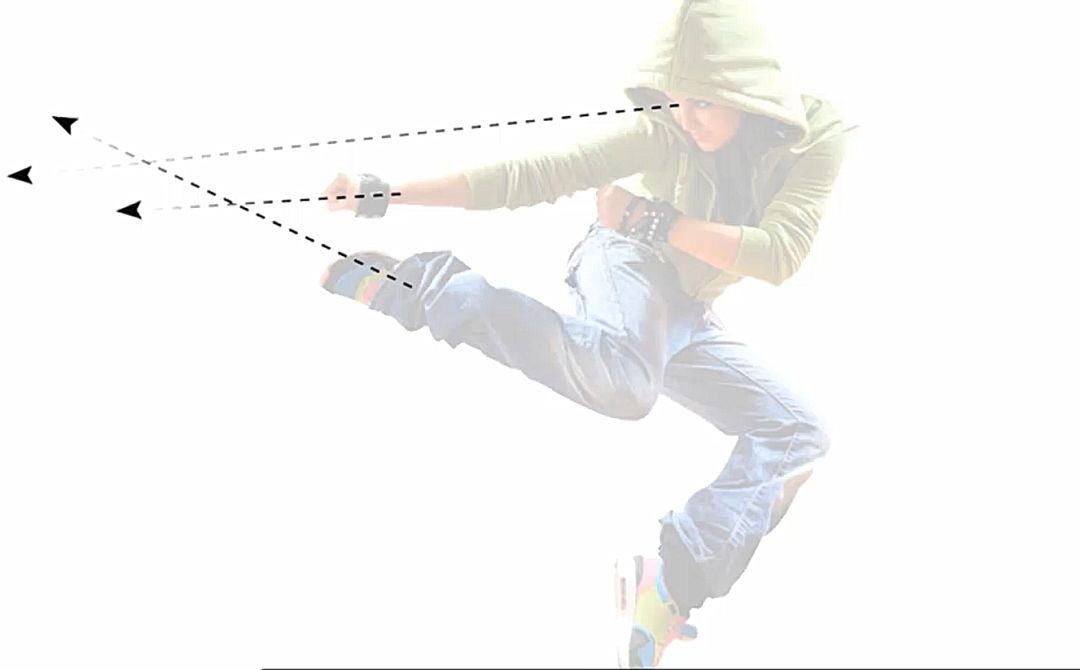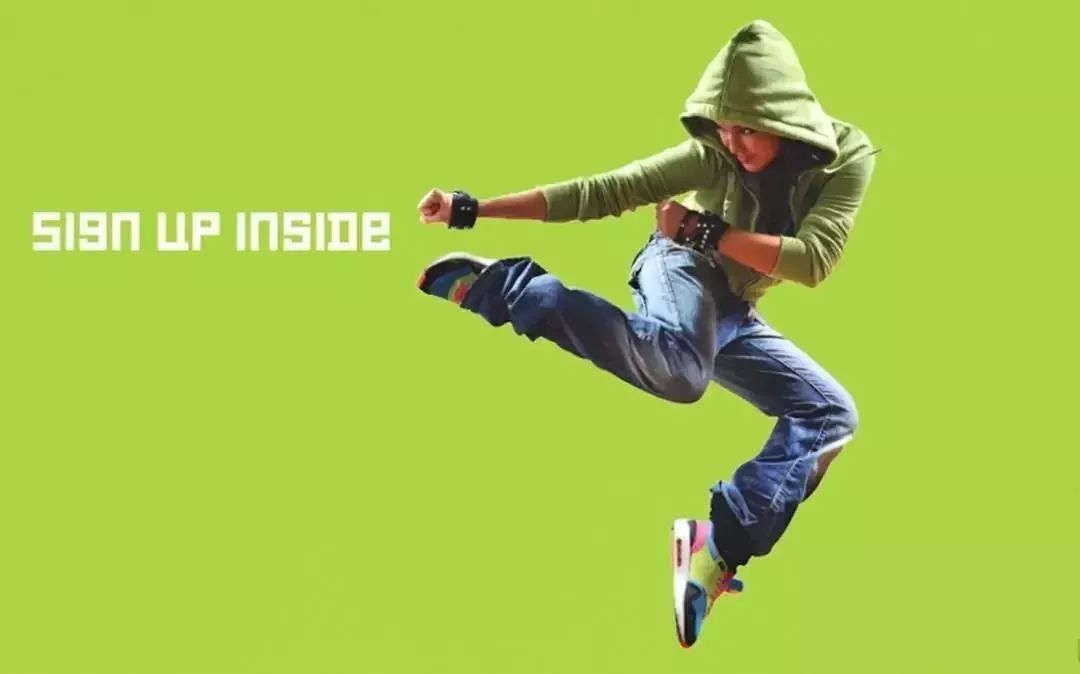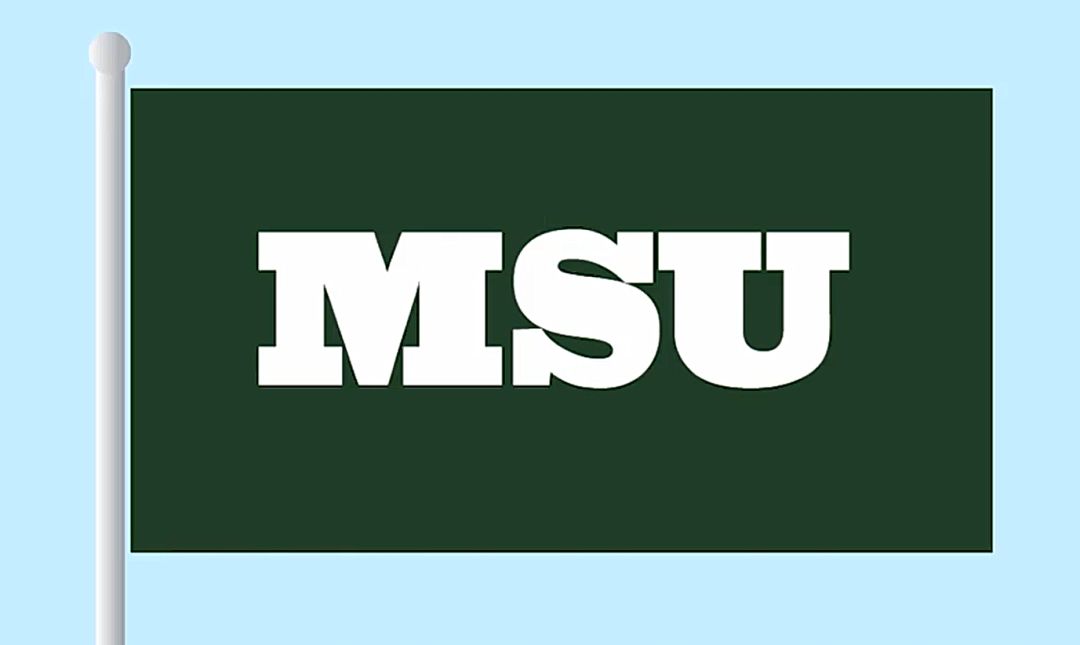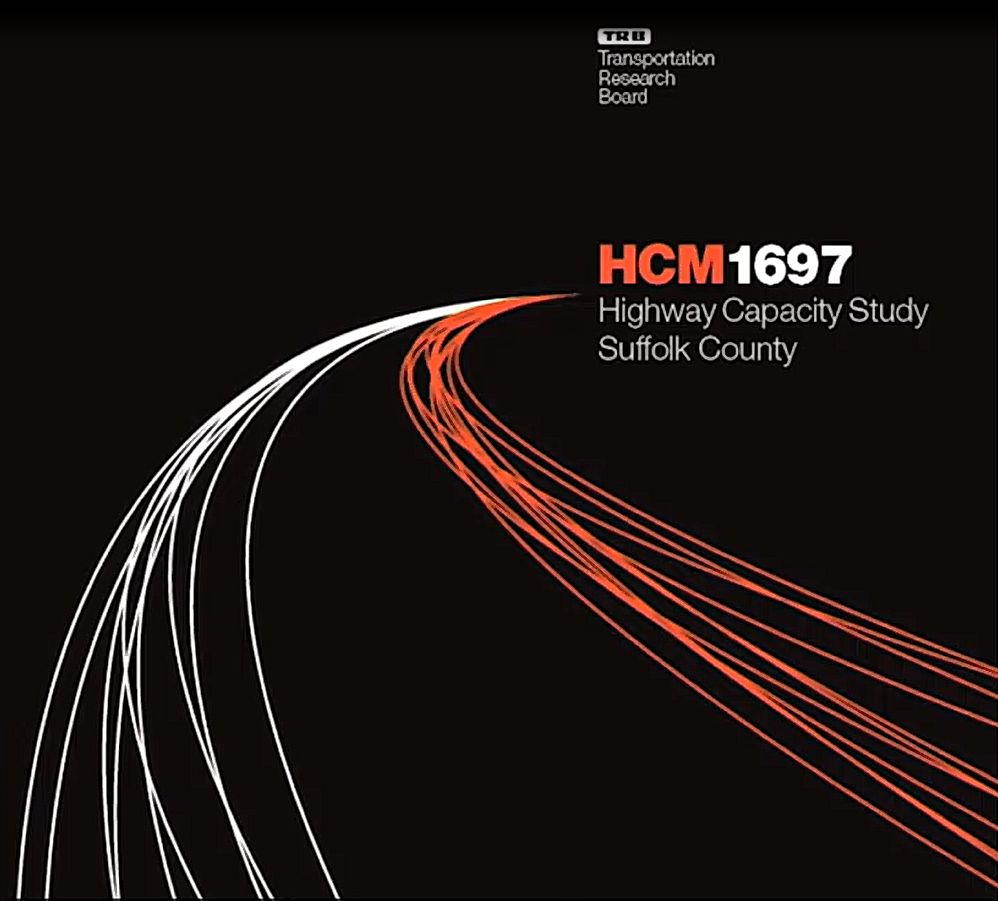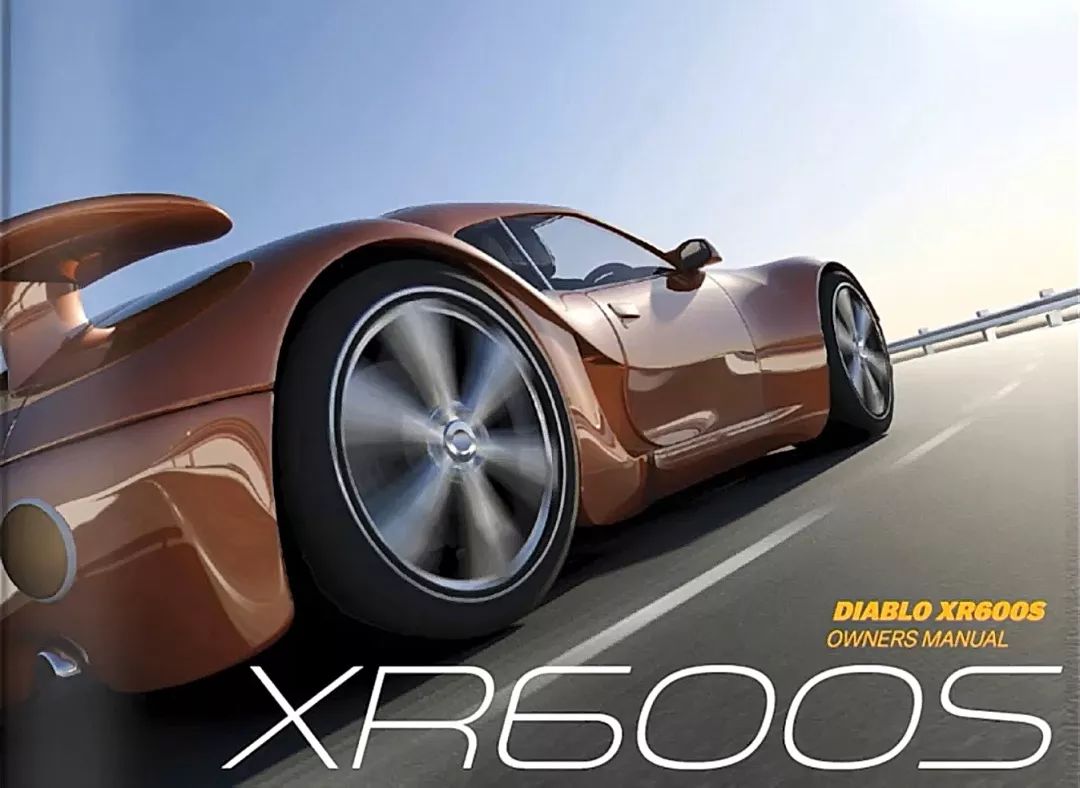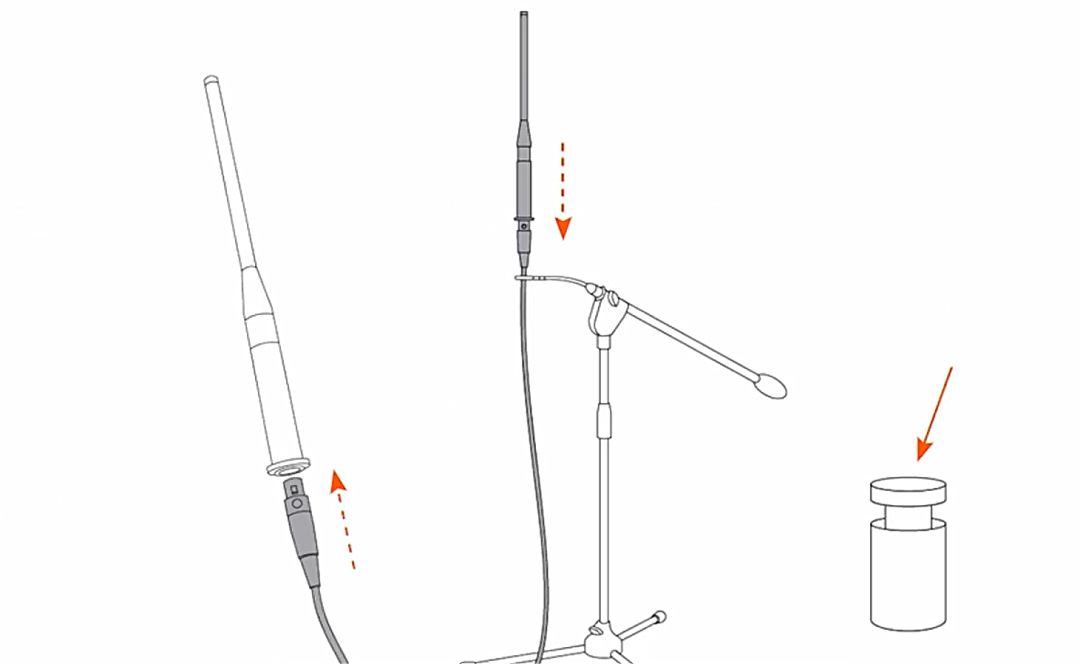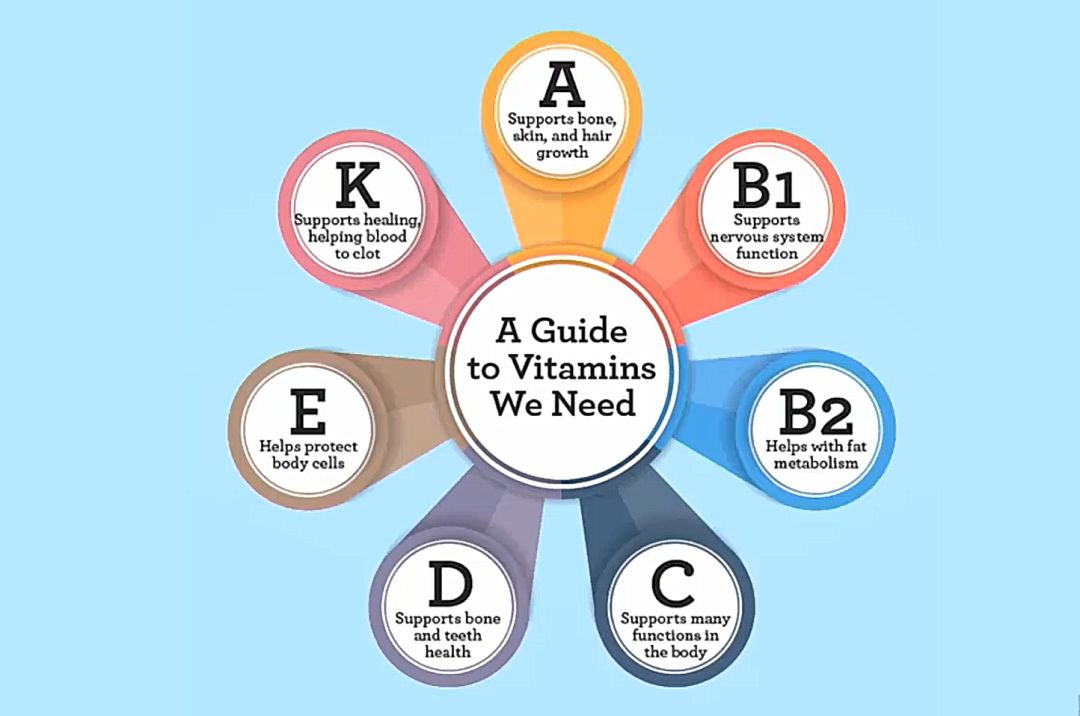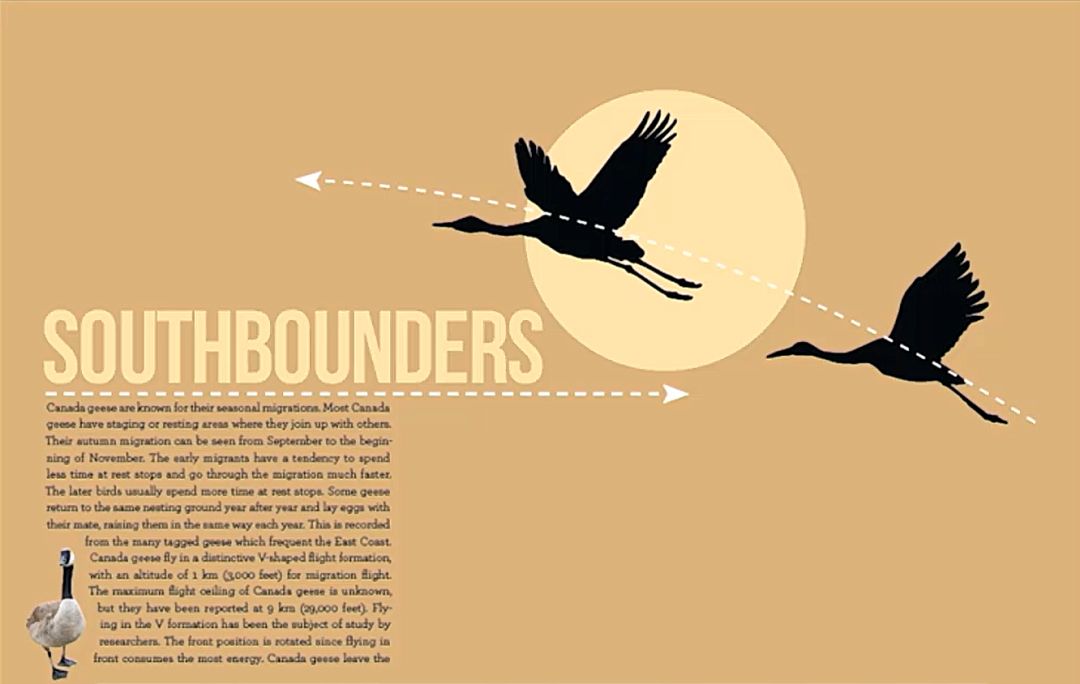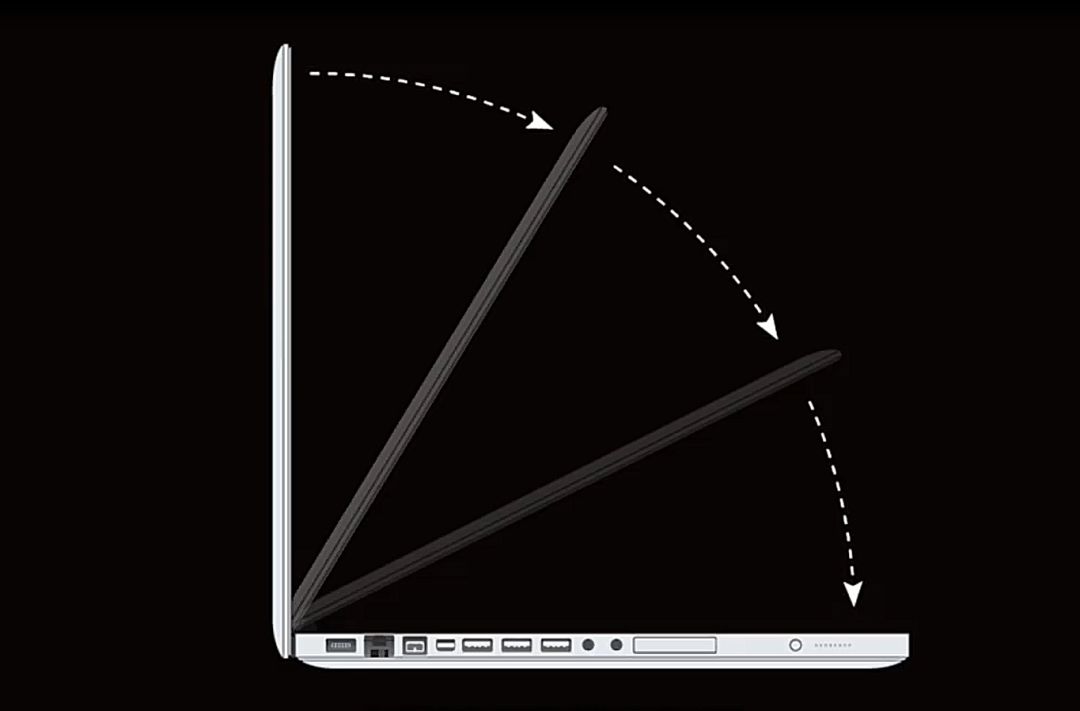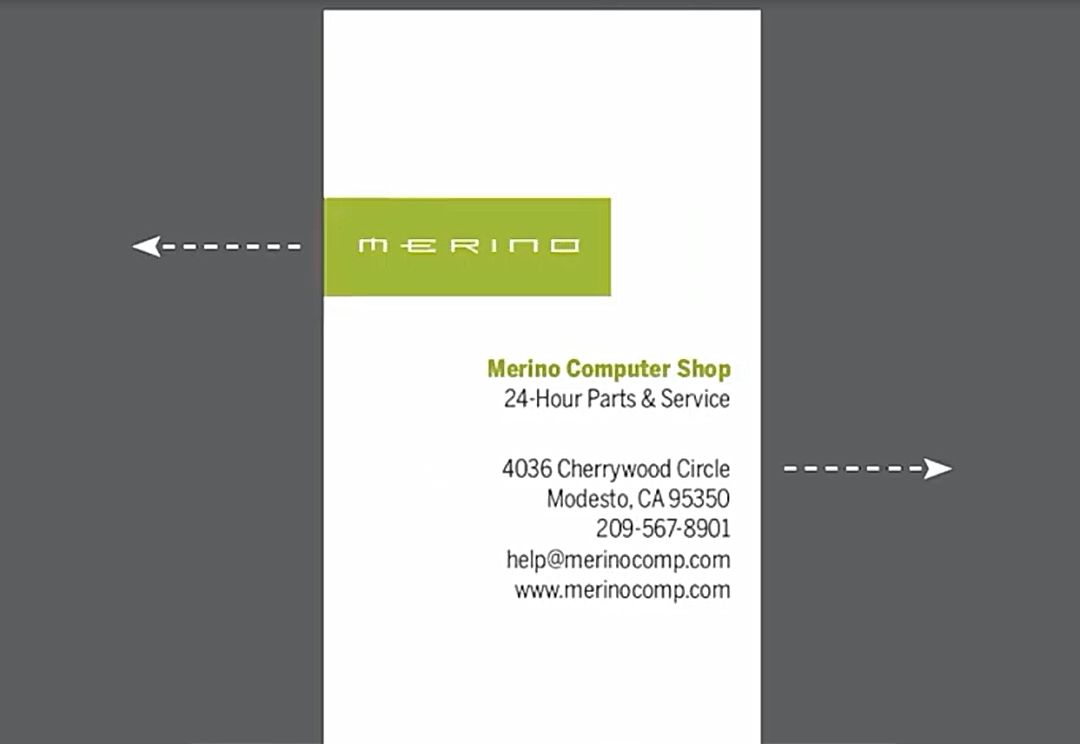
这 11 个设计小技巧,专门对付不懂设计的甲方
甲方:我想要的不是这种平淡的设计,而是更动感和酷炫的效果!”
很多不懂设计的金主爸爸并不吃极简主义这一套,他们要的就是酷炫,就是视觉冲击,下面这种调性的设计会更符合他们的口味。
这期,咱们就来聊一聊,让画面“动力十足”又容易过稿的11个小技巧~
01
动感图片的运用
动感图片的运用是最简单,也是最好处理的一种方法。
就像这张赛马图,它是在高速运动中拍摄的,本身就极具张力,再加上赛马的动作、疾驰的幻影更是将这张图片的动感推向顶峰。
找一张有动感的图片,只需加上一些文案,就可以快速形成一张极具动感的作品,就像这样。
02
韵律与假想
这张照片虽然是静态的,但是因为人体本身的韵律感,充满张力的肢体动作,以及延伸出去的假想线,让整个画面看起来动感十足。
仔细观察,图中女孩舞动的手臂以及腿部的线条,你会发现,视线在不知不觉中开始跟随着这些假想线的方向移动。
将这张图片作为元素,放入设计中。借助图中运动的力量感,就能形成一张富有动态感的海报设计。
除了上图的排版方式外,也可以借用刚刚谈及的假想线,通过动作指向,让观看者自然而然的看到所要表达的文案。
上图只是一个简单示范,实际操作中可以更加细致一些,就像这样。
借助假想线产生的巨大爆发力,将静态图片的动感效果推到了顶点。
03
视线走向的运用
平行视线轨迹
当页面上不再出现运动的状态时,那就要利用视线的走向去“说话”。
相信每个人在看到这幅全景图后,眼睛的状态必然是一个从左往右的运动过程。
想利用这种视线的走向运动进行创作,可分为三个步骤:
首先,创建一个从左往右的矩形条。
然后,在矩形条中添加文案信息。
最后,在右侧放上一张咖啡厅的图片,就大功告成了。
这样做的好处就是随着视线走向的运动过程,图像中,所有信息会自然而然的引导观看者,按照从左往右的顺序,依次读取图中信息。
扩散式视线轨迹
除了这种平行的视线轨迹外,星爆图又是另一种运动的方式——扩散式视线轨迹。
跟刚刚的全景图不同,人们的视线这次是以发射状从中间向四周逐步扩散。
利用扩散式视线轨迹的特征,可以将文案放置在图片中间,再将其按照前景线的方式逐步打开。
随着视线走向的从左往右运动,也让图像带上了动感的效果。这种动感并不是身体上的移动,而是思维上的迁移过程。
这个方法同样可以利用印刷术来表现。
这是一种有引力的设定,引导着观看者的视线的走向从左往后依次的移动。
04
汇聚线的运用
眼睛总是喜欢看着线条并跟着线条的方向去移动,特别是汇聚线,这里给大家介绍4种特殊的线条形式,它们能对信息起到很好的强调作用。
聚合线
聚合线,速度快,它可以带领人们的视野也从宽到窄依次变化,并在靠近窄端时做加速运动。
曲线
相对于聚合线来说,曲线的速度会更快。人们的目光不仅会随着曲线运动,还会在曲线末端的幻影中继续。并不会随着曲线的消失而立即收回视线。
像旋涡、发射线等多用曲线进行表达,它可以为版面带来更多的运动信息。
车道行轨线
车道行轨线,能将观看者的目光轻易汇聚至标题处,更有利于信息的强调。
齿汇聚的轮线条
利用汇聚的齿轮形成了天然夹角,让眼睛跟着汇聚线的方向转动,这是强调信息的另一种方法。
除了上面这些特殊的线条能对信息起到很好的强调外,有一些特殊的图形,也能起到同样的作用。
当这面旗子以矩形的形式出现时,它给人的感觉是完全静止的,但是,如果改变了旗子的形状,比如变成了三角形,跟刚刚的旗子相比动感会不会更强了一些?
这是因为眼睛会随着这些汇聚线不由自主的移动,如果再将旗子换个方向,这些汇聚线也会随着旗子变换而做出相应的调整,只不过跟刚刚相比,运动的速度就慢了许多。
05
倾斜的汇聚线
图片
图片的角度也常常会创造运动的过程,当目光跟随着这些建筑线条倾斜时,就有了倾斜的汇聚线以及不稳定的线条能量。
如果说上图显示的能量还不够明显,那么接下来的这张图就能更好的说明倾斜的汇聚线所能造成的动力感。
相比汽车在水平面上的状态来说,当特殊的视角形成了倾斜的汇聚线时,画面的速度感会更快。
在图片的基础上,再将文字也变得有一定的倾斜角度,那么,页面上的所有内容都在快速移动的状态下进行。
文字
文字,之所以能在下面环境中产生动感,那是因为图片中的字体是一种扩展型字体,所以观看者的目光不得不从左往右依次移动。
如果,再将字体做了倾斜处理,动感也相应的变得更加强了一些。
除此之外,适当增加一些模糊效果,也是增强动感的不错选择。
但是,这种方法还是要慎用,因为这样做会让字体的辨识度降低很多。
当然,也并不是所有的倾斜体都会让画面感受到速度的动感,就像文本框中的斜体,它就不会。这是因为,文本框中字体的主线不是水平的,而是垂直排列的。所以这里的斜体只是用于强调,或者作为一个样式要素出现。
06
假想线的设定
速率线
先来观察一辆小卡车
这时,你也许还分辨不出,它究竟是停止状态还是行驶的状态,如果这时,将小卡车做倾斜处理,它的“动感”会不会好了一些?
如果再加上假想的速率线,那么这辆小卡车的速度就更快了,甚至会让人想起了,前面介绍的赛马图。
当然,让卡车偏离画面的中心也是个不错的选择。有种疾驰幻影的感觉。
除上面这些,这里还有另一种方法。
虚线
看看这只小蜜蜂,它本身的动作并不具有动态特征,但是通过后面假想线的强调,让观看者仿佛看到了它运动的轨迹。就像这样。
甚至于可以用假想线中圆点的密集程度,去表现这只蜜蜂移动的速度的快慢。
箭头
充分利用箭头的指示功能也是个不错的选择。它能让物体有种因为跟随着箭头移动,而产生的动感。
以左边为例,根据箭头的指向,两个原本分开的部分好像真的即将合并在一起。中间的麦克风也将卡入支架中去,而右侧的实线只作为这一部分的指示作用而已。
当这种布局方式运用在一个静态页面之中,也会让这个静态页面充满着动态因素。就像下图这样。
发散
有时页面中的圆圈,单看它是静止的,但是当它从中间向四周发散时,这个图像就有了更多的动感。就类似于前面星爆的例子一样。
这是因为汇聚线让所有的元素都向内靠拢,增强了画面的动态感。
顺序性的排列
任何时候,将事物按照类似逐帧动画的顺序排列,也能增强画面的动感。
这种明显的连续性,能让人觉得,画面中好像真的有东西在动。
所以,当你想展示某个东西的运作原理时,就可以利用画面中元素顺序排列的方法。它不仅能让画面的动态效果更强,还能进一步强调物体运作的顺序。
重复性元素
当一个相同的元素,不停的重复出现时,它就能创造出一定的动感。就像这种情况。
穿过画面中红酒的水平线,形成一条从左往右的假想线。
将这五个看似独立的元素,以这样重复的形式摆放在一起时,就产生了动作与动感。这是一种极具吸引力的排版方式。
看个案例
第一步,准备一样空白的纸张,并在上面放置一张照片。
注意,这里是放上一张照片,不是放大照片。并且,将这张照片要不断的重复摆放。这种感觉有点像商场里的电视墙。
有趣的是,虽然所有的照片都是一样的,但是观看者的目光,却会随着这些照片,不停的在这个范围内移动。此刻的观看者,像是图案的探索者,不断寻找着每个画面中的不同之处。
这时,观看者的眼睛一定十分忙碌,而很多动作也就在此刻,从观看者的眼中创造出来。
第二步,在卡片右侧添加上不同字体的动作。例如这种叫做Hairspray的花体字,这样做,视线同样会被字体中的线条二次吸引。
再来整体的欣赏一遍,看看是不是上面提及的这种感受?
07
花样图案
花样图案通常也可以产生动感,因为它本身具有很强的运动性。
就像上图这样,一排排大嘴鸟面朝相反的方向,由于鸟的嘴巴就是一个类似于假想线的指示器。所以,它会让观看者在浏览时,不自觉的跟着这个指示器移动,向左看,向右看,向左看,向右看…
这样的花纹图案,让画面显得非常生动,充满活力。
08
顺序与走位
充分利用版面中元素的位置顺序与走位,可以创造出一定的动态感。
像上图中的这个版式中规中矩,将所有的内容都摆放在中间。因此观看者所有的目光也都集中在了中心位置。
这也正是因为这个版式是静态的,所以它给人的感觉会更加稳固。但是如果你想创造一个更有活力的排版,那就应该在危险边缘试探,避免中心点。
下面我们运用画面中元素顺序与走位的方法,让版面充满动感。
方法一:
将名字放在左边,文本放在右边,这样作品的版式上就造成了一种不对称的张力。这时,观看者的目光要么往左边看名字,要么往右边看文本。
这样一来,这张卡片的动作就多了起来,设计也会更加有力。
方法二:
现在再来尝试第二种方法,将所有的元素都置于画面右侧。
这样的效果也能造成不平衡感,从而使卡片有了更多动感。因为它处于卡片的最右端,对动作有强调作用。
上面这种方案有一点要注意。画面中有一个绿色的标题框,如果你在字母O的旁边画一条辅助线,就会发现下面的文本和字母O都是在同一条辅助线上。因此所有的文本都是向右侧对齐的。
09
透视视角
透视和汇聚线一样,能够营造出移动的效果。
这是一副从前往后依次排列的纸牌。如果纸牌中每一张的显示量都少了一些,那么随着它逐渐变小,你会感觉到,在这里有一条直线的存在。
再或者,当纸牌越来越小,而每张卡片显示的宽度都相同,就会产生一条曲线。
无论是上述的哪种情况,观看者的目光都会被一条有力的线条牵引着,就像前面的汇聚线一样。
如果随着物体越小颜色变得越浅,就会产生一种透视感。物体越远就与背景越相似。
透视感的使用也常常用于在海报中,它可以很好地表明元素之间的前后关系。
10
压缩与叠加
对空间进行压缩处理,也是建立动感的一种方式。
下面这幅图只是对单词进行了简单的摆放,整个画面毫无动感,针对这个问题,应该如何重写设计。
第一步,对单词进行简单的上色。
第二步,将所有的字母挤压到一起,重叠排列。
第三步,将字母设置为正片叠底过滤模式,以便能更清晰的看透字母。
这样,诸多的动感,就被互动式的排列在了字母之间。
当然这里也有一些需要注意因素:
1、必须使用普通字体,并且将字体加粗才能起到这种效果。因为当字体很纤细的时候,会因为太过单薄,而达不到想要的效果。
2、字母不能太过杂乱,否则两个字母之间会形成一些奇怪的形状。
3、字母形状不能太过相似或者太窄。
注意好以上这三点,那么,这个方法的运用效果还是很不错的,就像下面这样。
11
图像偏移
想要运用偏移图像的方法,主要有两个步骤。
第一步,设置字体,轮廓描边,偏移轮廓。
第二步,创建第二个轮廓,然后进一步的将其偏移。
这是一种生动有趣的方式,它可以创造有力的动感。